Die folgenden Auszüge stammen aus der Jenaer Liederhandschrift (Zitation: ThULB Jena, Ms. E. f. 101, Bl. 080r und 080v). Wir zeigen den Weg vom Original über das harmonisierte Mittelhochdeutsch bis zur modernen Schrift — drei Stufen einer Annäherung an ein Lied, das vor 700 Jahren entstand.
Loibere riesen
Witzlaw von Rügen (1265–1325) — Dieses Lied ist, neben vielen anderen, in der Jenaer Liederhandschrift überliefert. Es bietet die Möglichkeit, sich einem mittelalterlichen Werk zu nähern. Ohne Takt- oder Tempoangaben und mit nicht eindeutigen Notenwerten kann eine heutige Interpretation nur eine Annahme sein.
Jenaer Liederhandschrift
Drei Stufen einer Annäherung
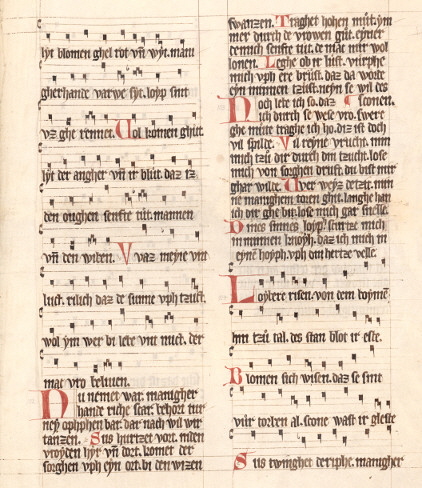
Originalschrift
Pergament aus dem 14. Jahrhundert
Auf Pergament tanzen Quadratnoten über vier Linien, darunter steht der mittelhochdeutsche Text. Initialen und Zierbuchstaben heben Strophen hervor — eine Seite, in der Schrift, Musik und Buchkunst untrennbar verschmolzen sind.
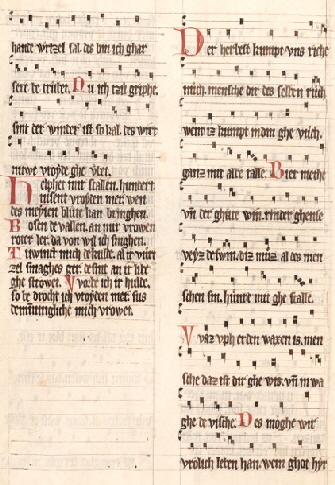
Harmonisiertes Mittelhochdeutsch
Lesbar gemacht
Der zweite Blick gilt einer harmonisierten Fassung: Mittelhochdeutsch in moderner Orthografie, damit das Lied auch ohne Spezialkenntnisse zugänglich wird. Verse, Reim und Versmaß bleiben — nur die Buchstaben rücken näher an unser Auge.
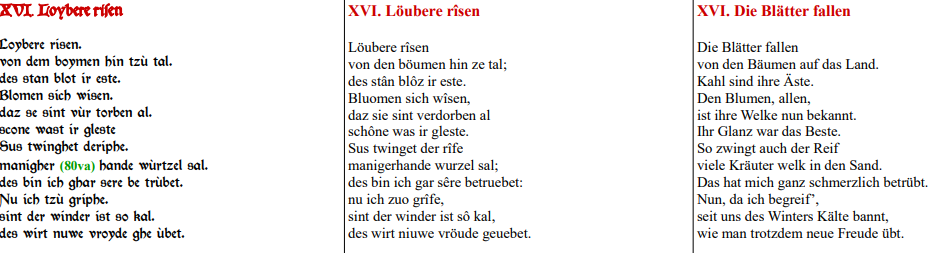
Moderne Schrift
Ein Lied wird wieder singbar
Die dritte Stufe übersetzt das Lied in heutige Notenschrift und neuhochdeutsche Sprache. Aus der mittelalterlichen Andeutung wird eine spielbare Vorlage — mit dem ausdrücklichen Vorbehalt, dass Tempo und Rhythmus eine Vermutung bleiben.